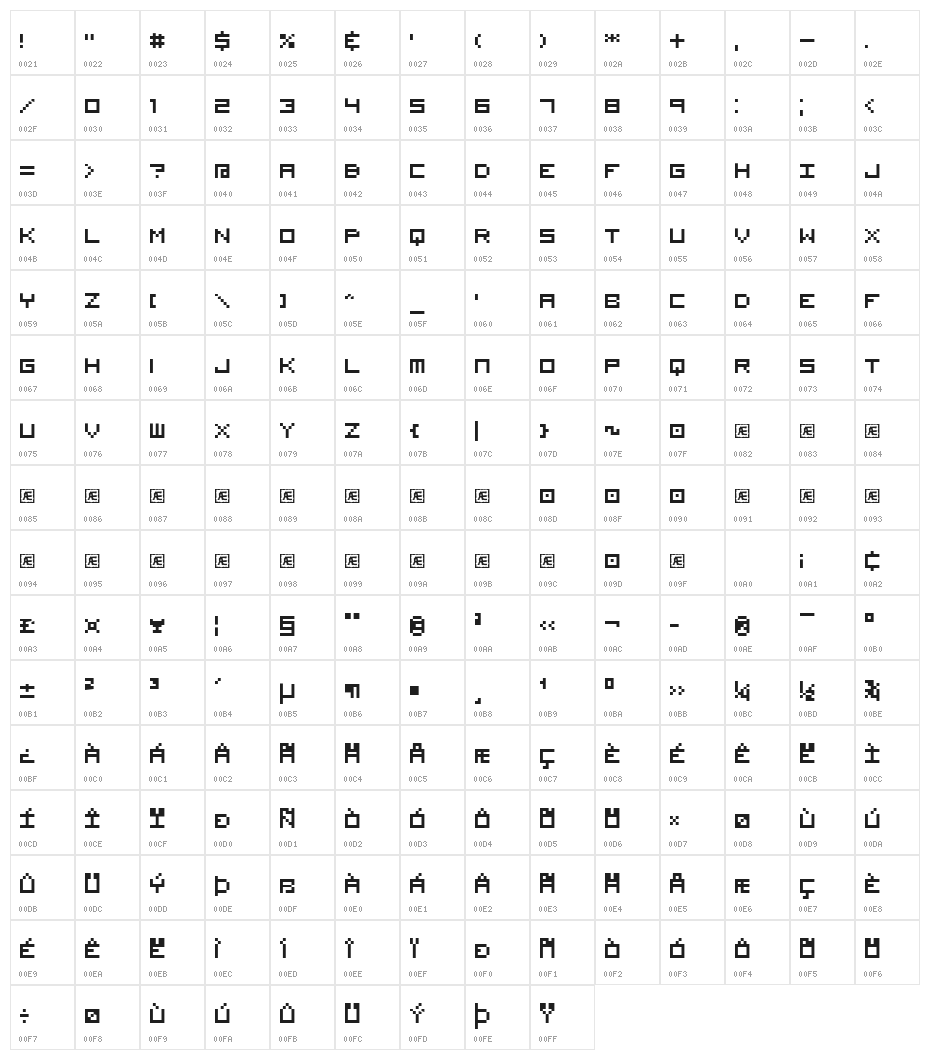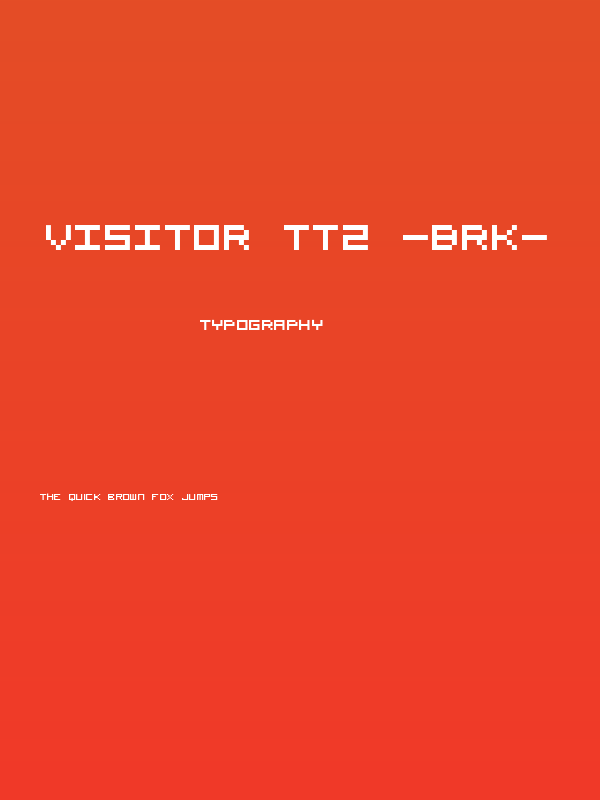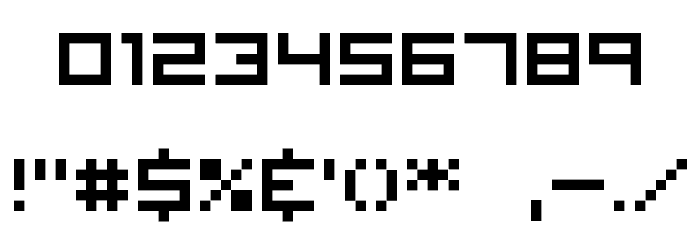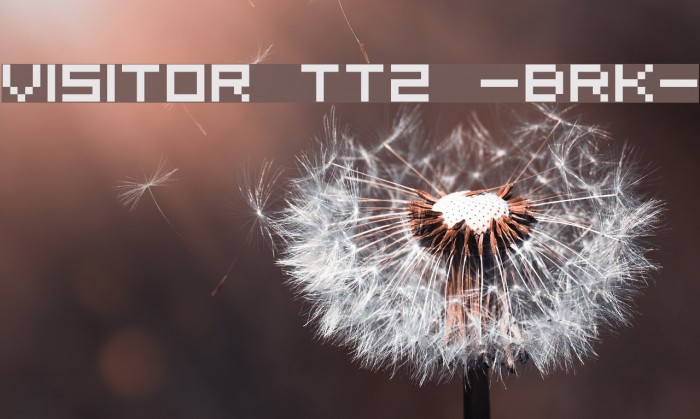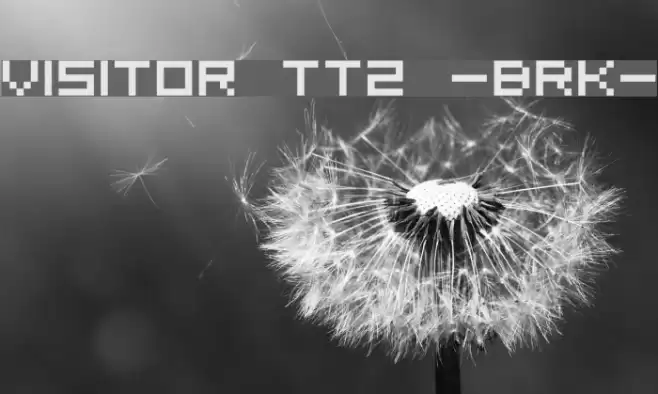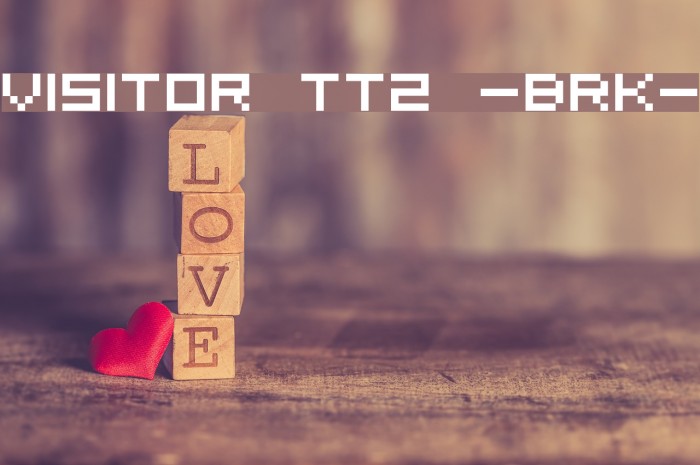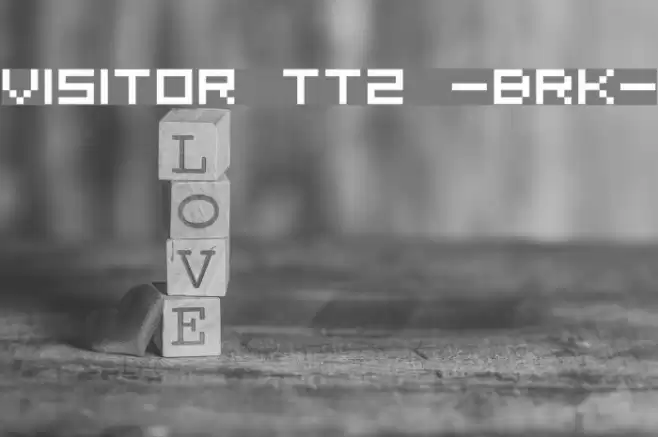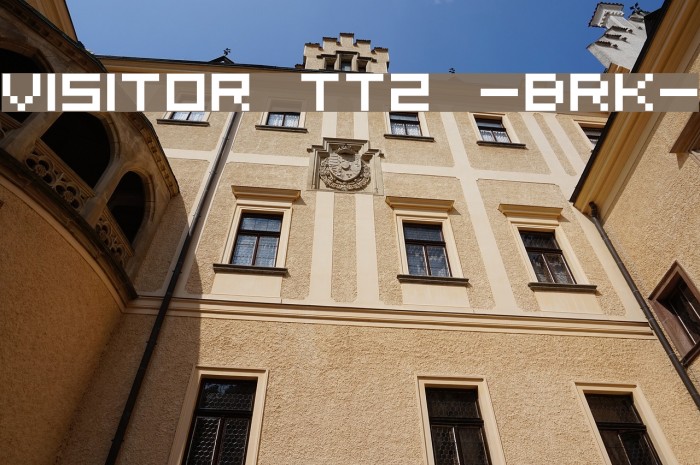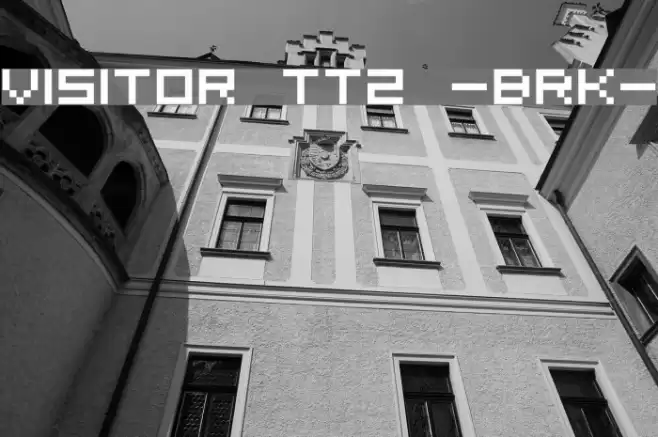
Visitor TT2 -BRK- Font
| النمط العام | Vintage |
| مشاريع مقترحة | Ideal for retro video game designs, digital art projects, tech-themed posters, and any creative work that seeks to evoke a nostalgic digital feel. |